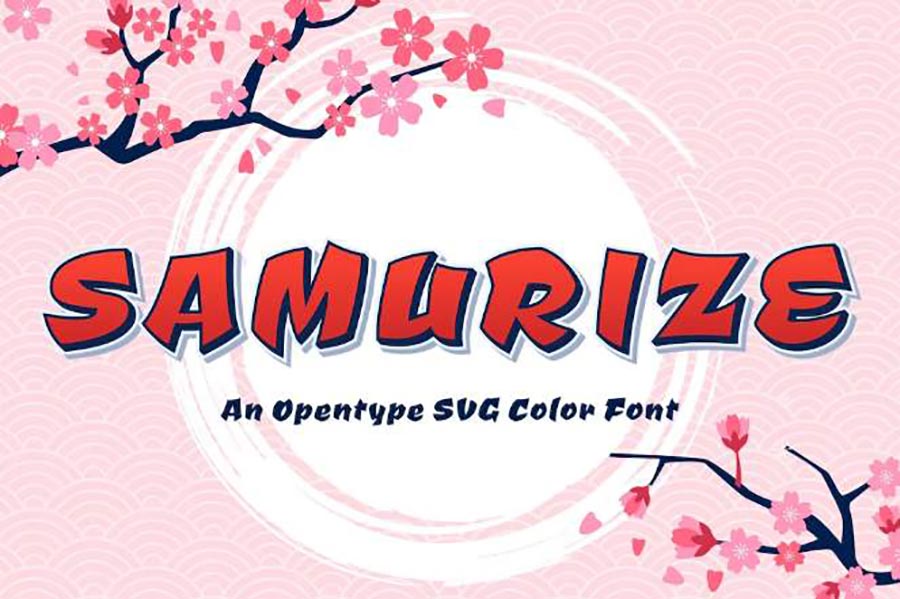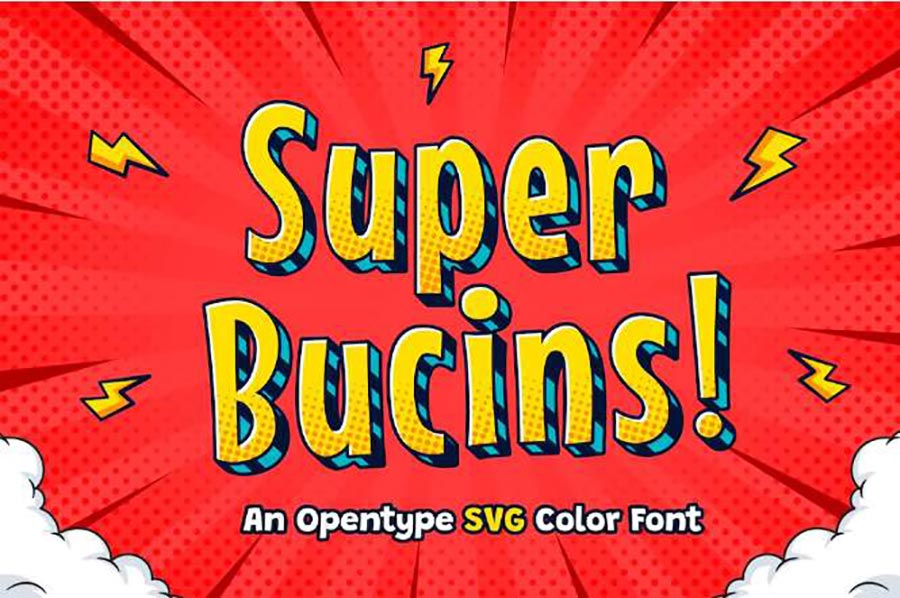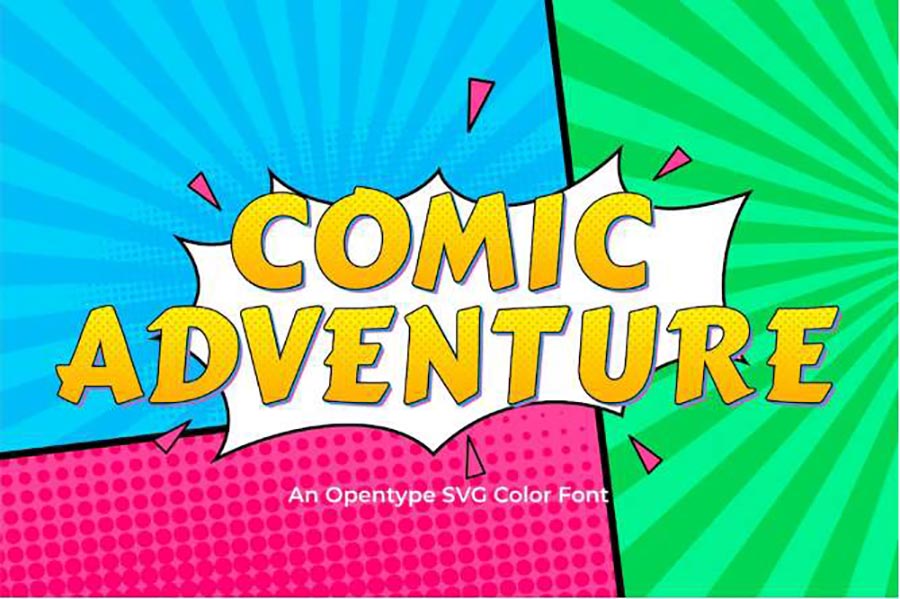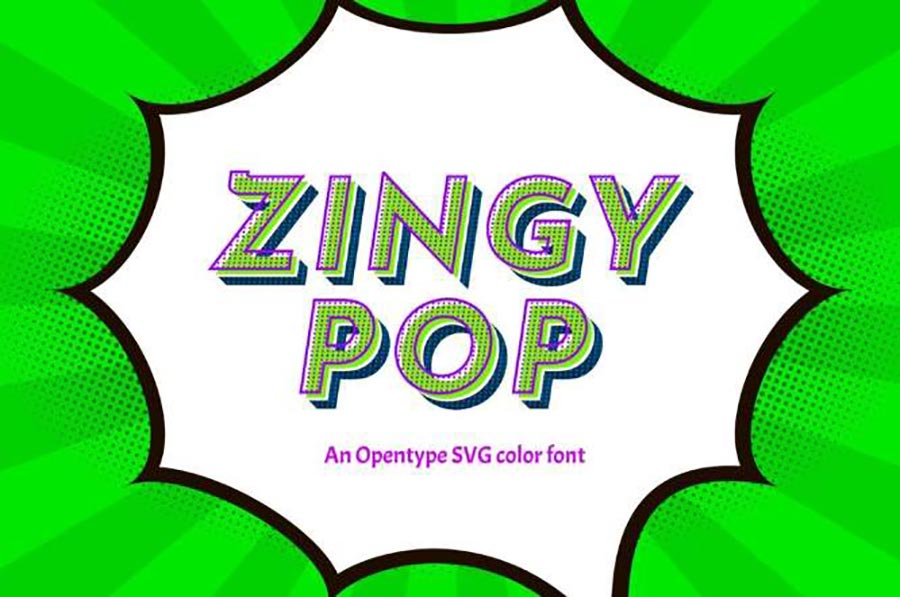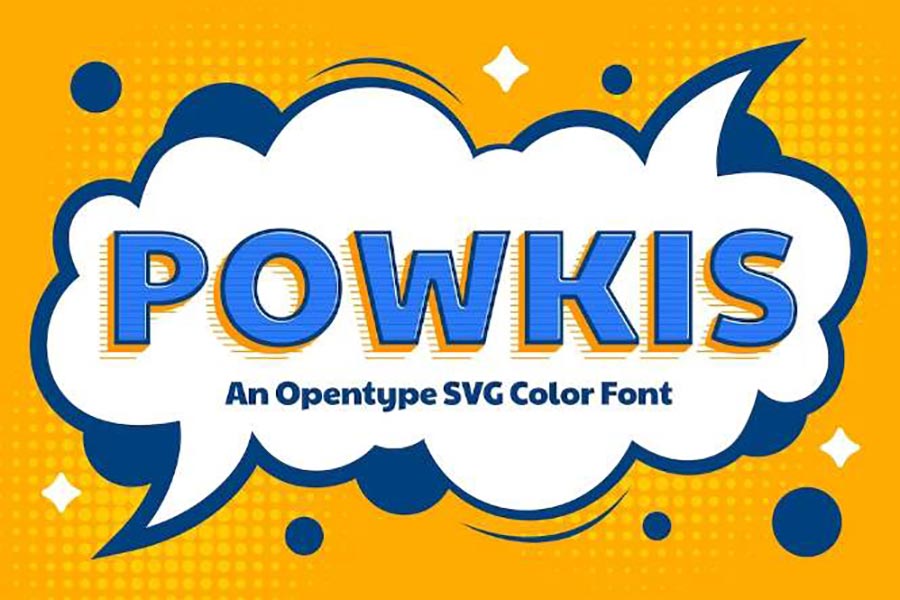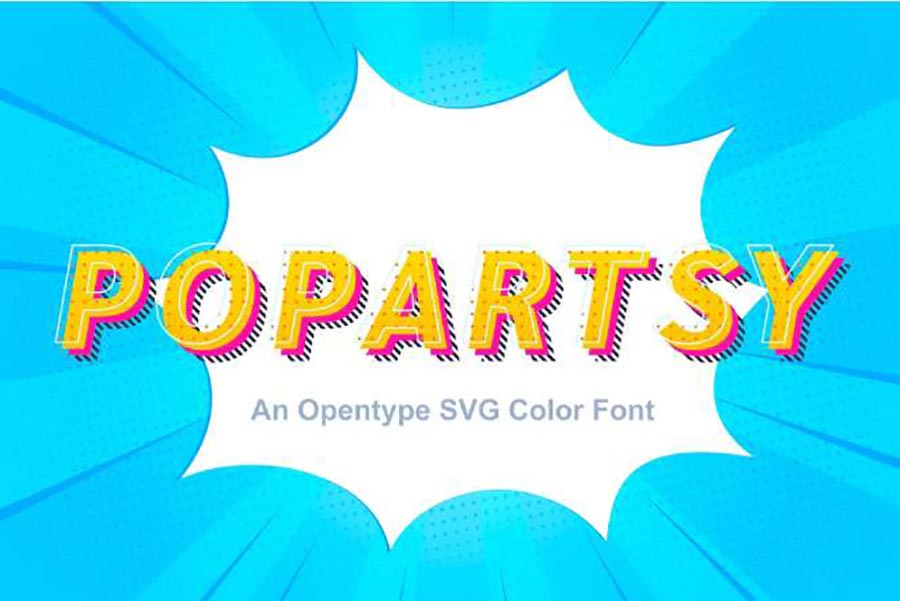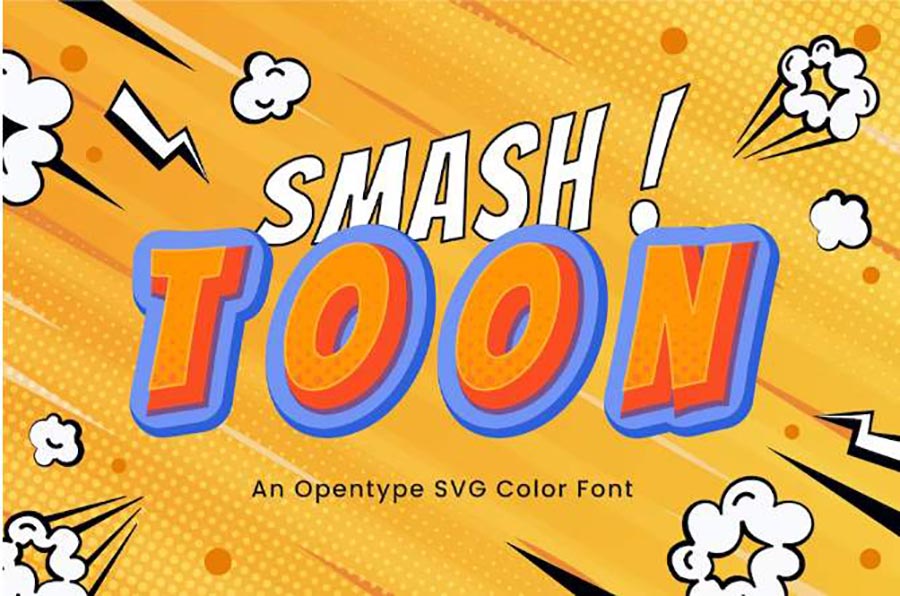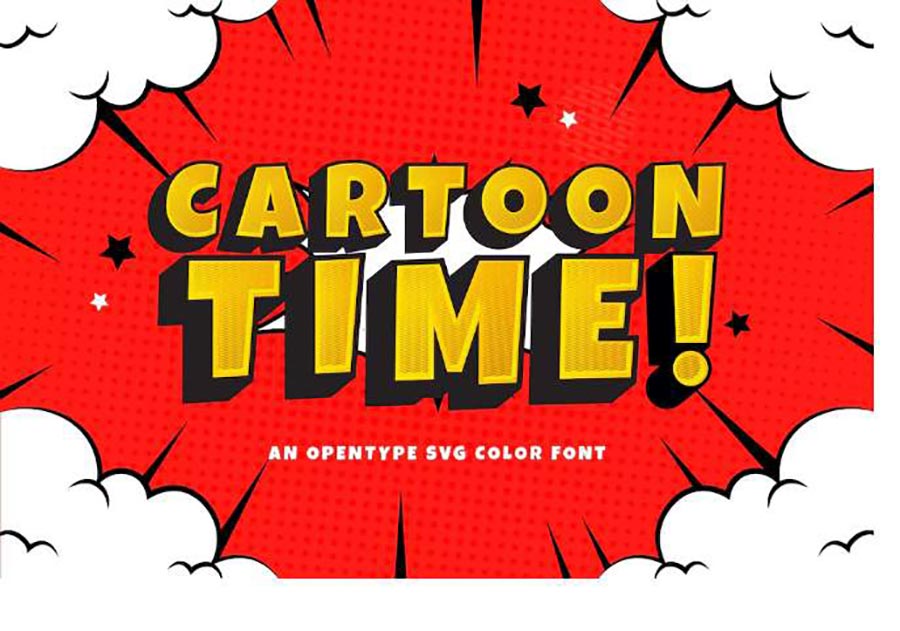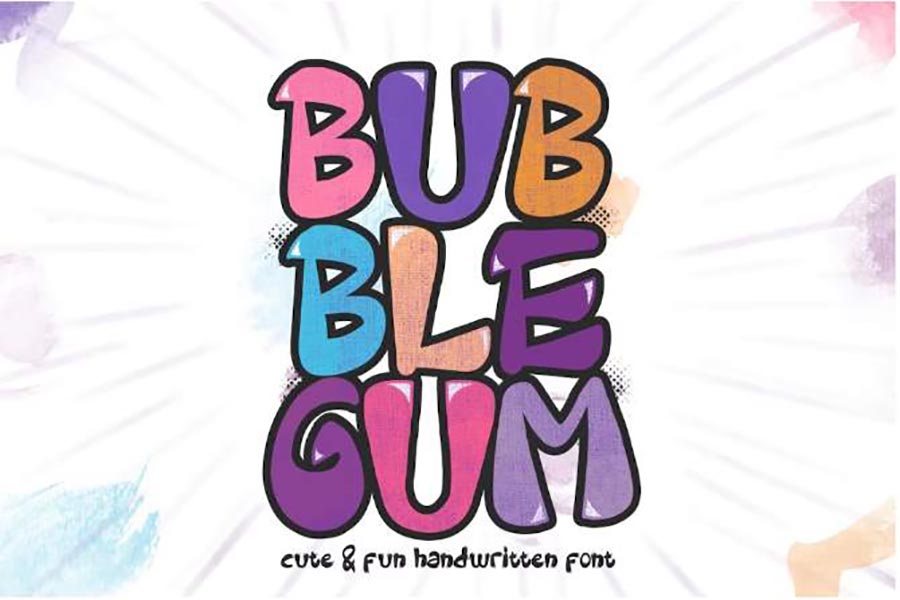
Hướng Dẫn Tải Miễn Phí 10+ Font chữ Comic Cực Đẹp
Bạn đang tìm kiếm những font chữ comic độc đáo và miễn phí để làm nổi bật dự án thiết kế của mình? Hãy cùng khám phá bộ sưu tập hơn 10 font chữ comic cực đẹp từ sadesign.vn, nơi cung cấp các tài nguyên thiết kế chất lượng cao và hoàn toàn miễn phí.
Font Chữ Comic: Điểm Nhấn Độc Đáo Cho Thiết Kế
Font chữ comic luôn là lựa chọn hàng đầu cho những thiết kế mang phong cách vui nhộn, sáng tạo. Chúng không chỉ giúp truyền tải thông điệp một cách sinh động mà còn tạo ấn tượng mạnh mẽ cho người xem. Với sự phát triển không ngừng của ngành thiết kế, nhu cầu về font chữ comic ngày càng tăng cao.
Tại Sao Nên Chọn Font Chữ Comic?
Font chữ comic không chỉ mang lại sự mới mẻ mà còn giúp tăng tính tương tác và thu hút sự chú ý. Đặc biệt, trong các dự án liên quan đến trẻ em, truyện tranh hay các sản phẩm giải trí, font chữ comic đóng vai trò quan trọng trong việc truyền tải cảm xúc và ý tưởng.
Lợi Ích Khi Sử Dụng Font Chữ Comic Miễn Phí
Một số mẫu font chữ comic tại Sadesign:
Kết Luận
Font chữ comic là một công cụ tuyệt vời để làm nổi bật dự án thiết kế của bạn. Với hướng dẫn tải miễn phí từ sadesign.vn, hy vọng bạn sẽ tìm được những font chữ phù hợp nhất cho công việc của mình. Đừng ngần ngại khám phá và sáng tạo để mang lại những sản phẩm độc đáo và ấn tượng nhất! hám phá cách tải miễn phí hơn 10 font chữ comic đẹp mắt từ sadesign.vn. Nâng tầm dự án thiết kế của bạn với các font độc đáo, dễ dàng sử dụng và hoàn toàn miễn phí.